手抄报是新闻事业发展过程中出现的一种以纸为载体、以受潮形式发布新闻信息的报纸,现在的报纸来源就是手抄报。手抄报也是一种群众性的宣传工具。手抄报现在更多的呈现形式改为了电脑设计再进行打印出来,这种类型的设计既要容纳一定的知识内容,版面设计也要精彩美观。字体更是要有特色,美观大方、工整有序,并且易于识别字体,体现文字的魅力。
今天给大家介绍适用于三种不同风格要求的字体:
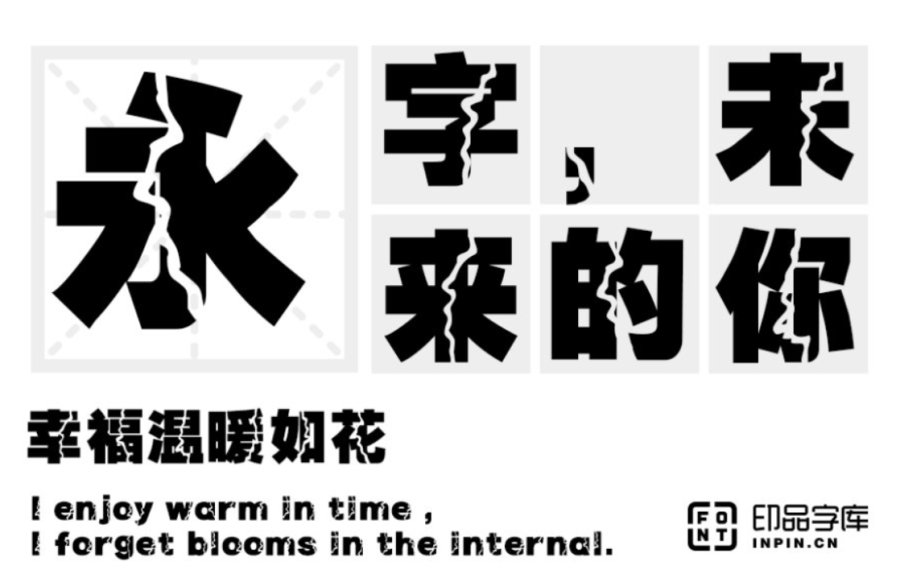
印品霹雳体:这是一款稳重但又富有创意的字体,平稳和谐,展现通上彻下的能量释放。笔画之间生动变化,刻画出列缺霹雳 丘峦崩摧的震撼感。字形雄厚有劲,应景感极强,作为手抄报字体新颖美观,还适用于广告创意设计、标志设计、包装设计、游戏等各类领域。
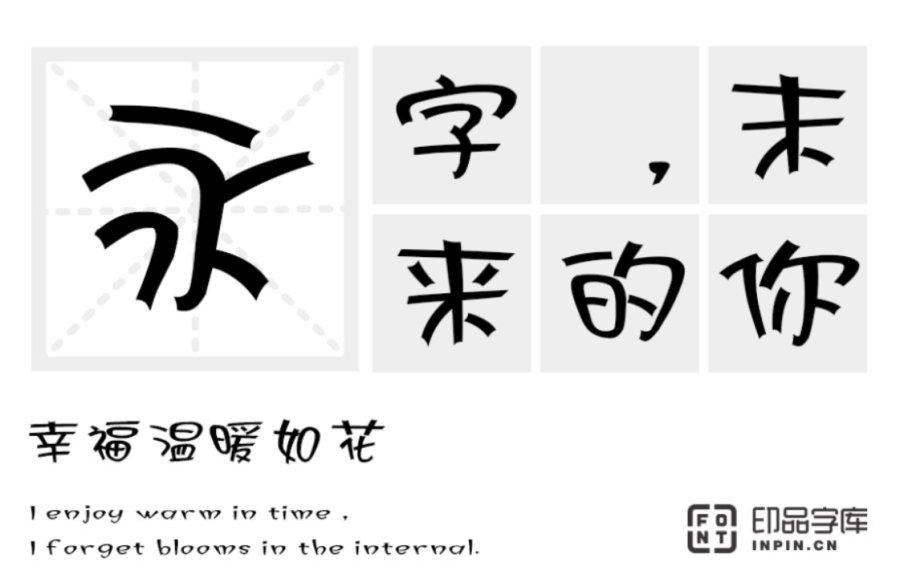
印品瘦身体:这是印品首款一键生成的字体,把原有字体做了瘦身,意在追求个性大胆尝试创新的理念。生动明亮,适合活泼轻快风格的板报,还适用于游戏、广告设计、包装设计、动漫、影视综等广泛领域。
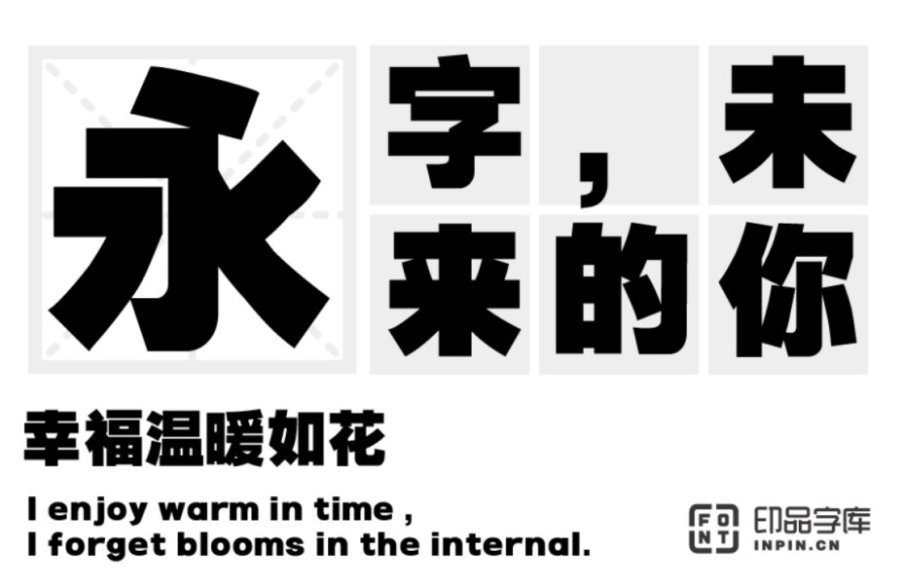
印品鸿蒙体:这款字体结构严谨端庄,字形饱满,字体间距布局均匀讲究 ,整体美观又大方,整体风格刚劲有力而又不失俊儒之风;笔画之中蕴含古朴沉厚端凝之势,在板报标题上有很大的应用空间。还适用于封面设计、logo、广告、屏幕显示等领域。